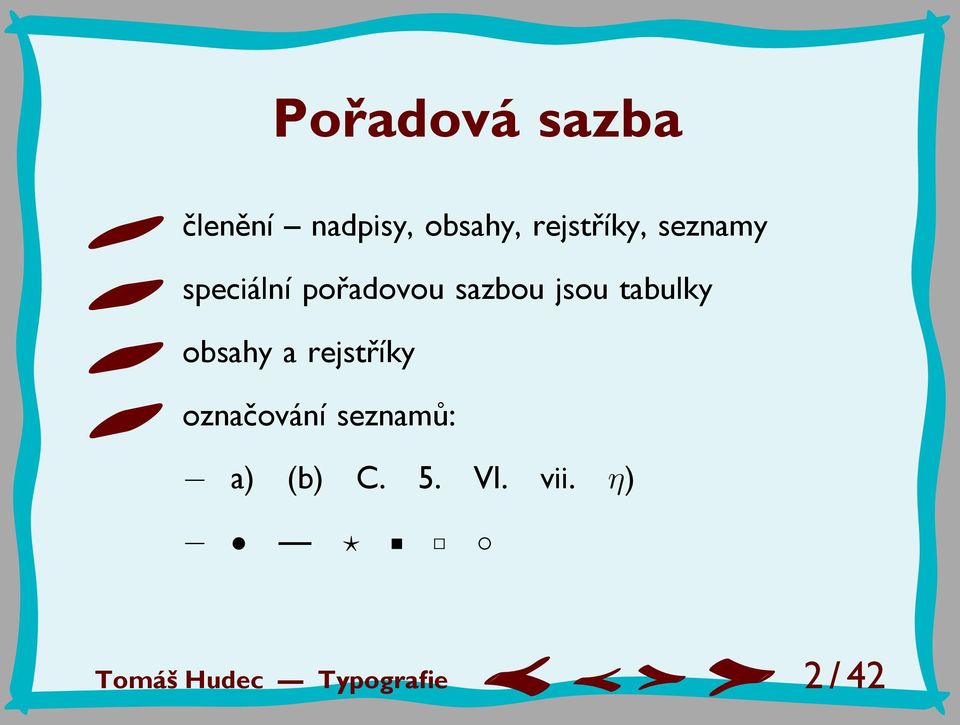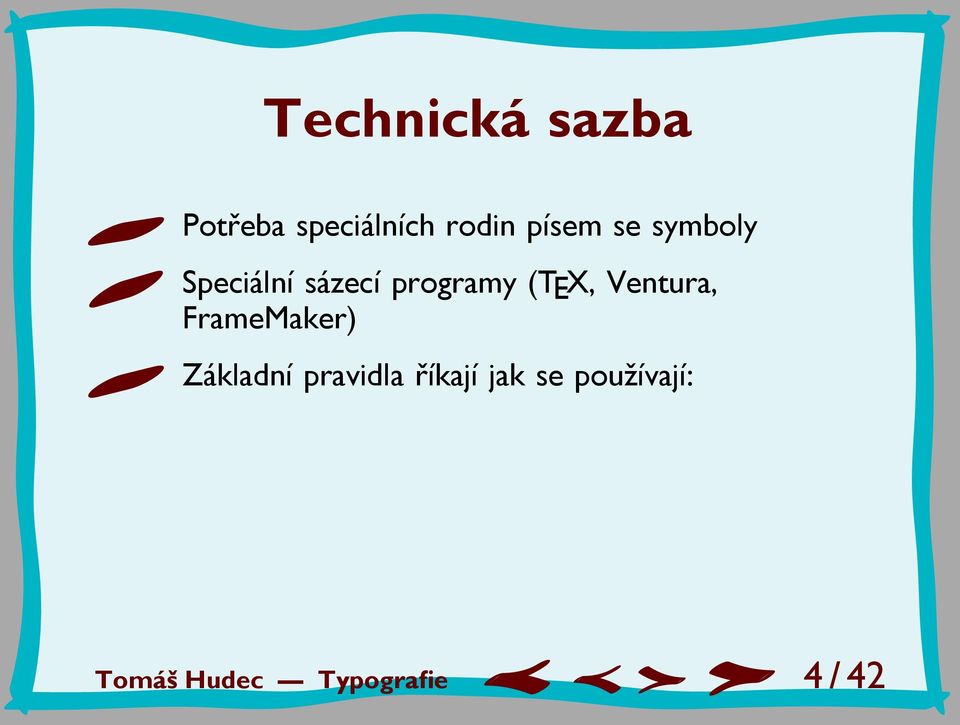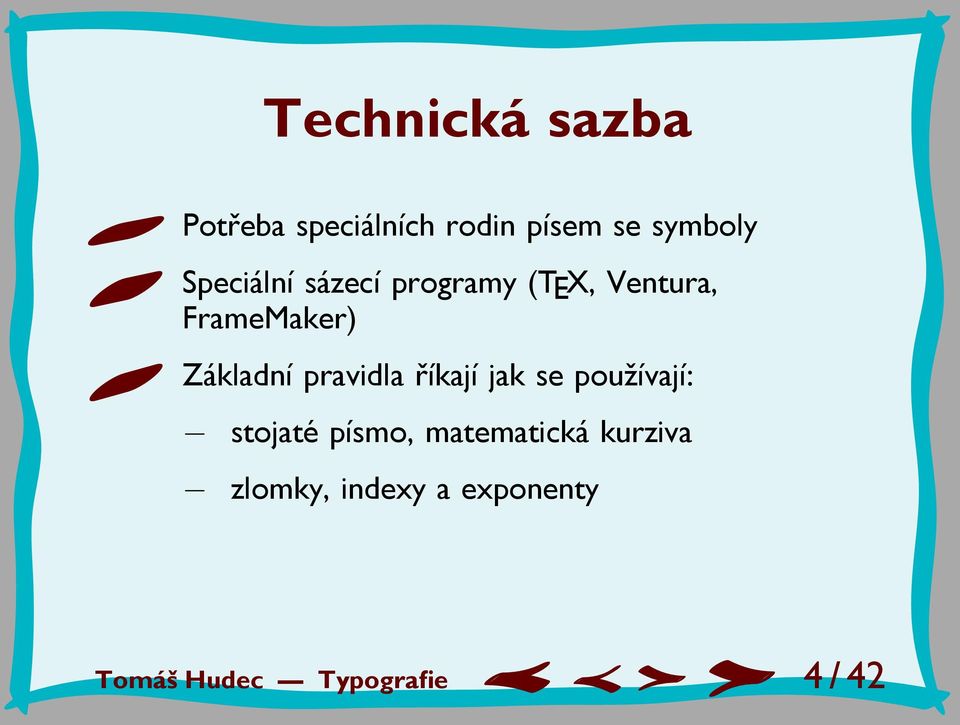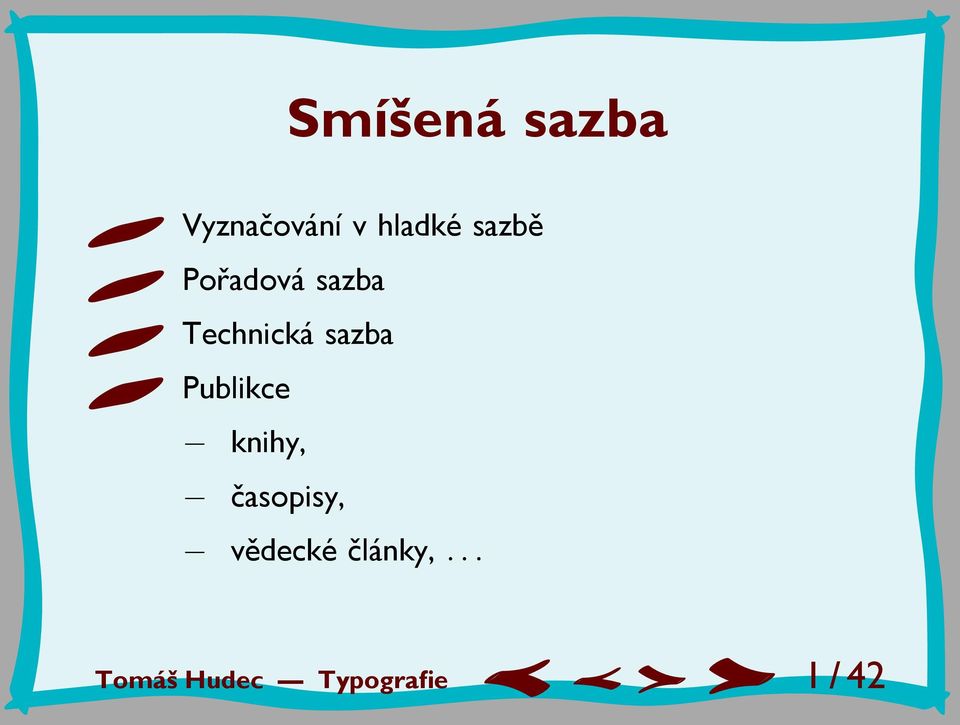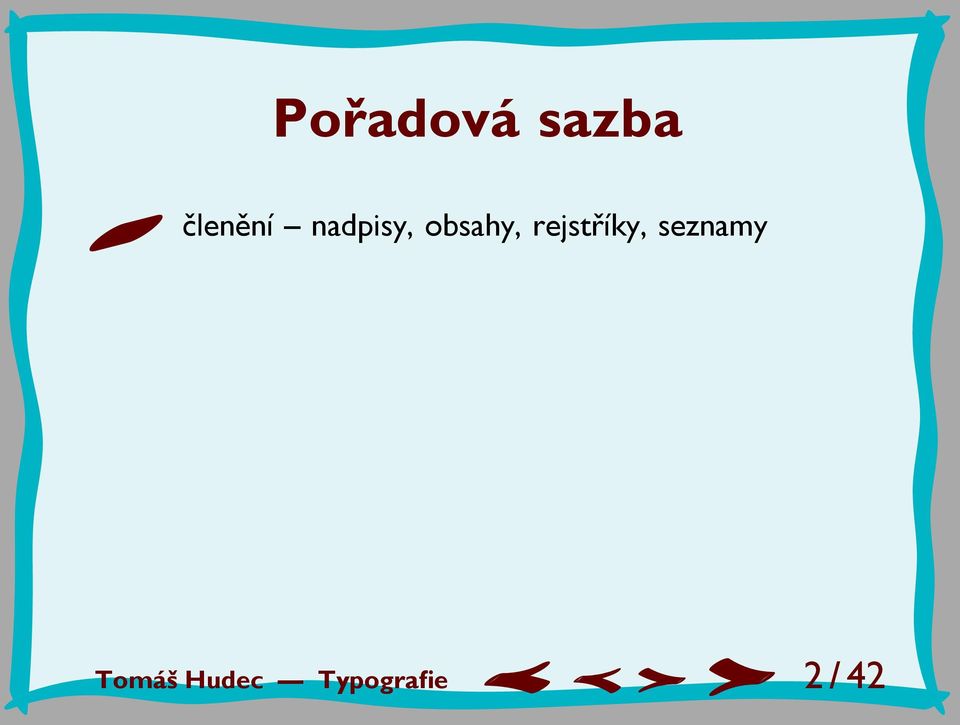
Typografie. Smíšená sazba, kniha
1 Typografie Smíšená sazba, kniha
2 Smíšená sazba Vyznačování v hladké sazbě Tomáš Hudec Typografie 1 / 42
3 Smíšená sazba Vyznačování v hladké sazbě Pořadová sazba Tomáš Hudec Typografie 1 / 42
4 Smíšená sazba Vyznačování v hladké sazbě Pořadová sazba Technická sazba Tomáš Hudec Typografie 1 / 42
5 Smíšená sazba Vyznačování v hladké sazbě Pořadová sazba Technická sazba Publikce knihy, Tomáš Hudec Typografie 1 / 42
6 Smíšená sazba Vyznačování v hladké sazbě Pořadová sazba Technická sazba Publikce knihy, časopisy, Tomáš Hudec Typografie 1 / 42
7 Smíšená sazba Vyznačování v hladké sazbě Pořadová sazba Technická sazba Publikce knihy, časopisy, vědecké články,... Tomáš Hudec Typografie 1 / 42
8 Smíšená sazba Vyznačování v hladké sazbě Pořadová sazba Technická sazba Publikce knihy, časopisy, vědecké články,... Akcidenční sazba Tomáš Hudec Typografie 1 / 42
9 Pořadová sazba členění nadpisy, obsahy, rejstříky, seznamy Tomáš Hudec Typografie 2 / 42
10 Pořadová sazba členění nadpisy, obsahy, rejstříky, seznamy speciální pořadovou sazbou jsou tabulky Tomáš Hudec Typografie 2 / 42
11 Pořadová sazba členění nadpisy, obsahy, rejstříky, seznamy speciální pořadovou sazbou jsou tabulky obsahy a rejstříky Tomáš Hudec Typografie 2 / 42
12 Pořadová sazba členění nadpisy, obsahy, rejstříky, seznamy speciální pořadovou sazbou jsou tabulky obsahy a rejstříky označování seznamů: a) (b) C. 5. VI. vii. η) Tomáš Hudec Typografie 2 / 42
13 Zarovnání seznamů Vpravo a) raz b) dva. m) třináct Vlevo a) raz b) dva. m) třináct 1. raz 2. dva. 13. třináct I. raz II. dva. XIII. třináct Tomáš Hudec Typografie 3 / 42
14 Technická sazba Potřeba speciálních rodin písem se symboly Tomáš Hudec Typografie 4 / 42
15 Technická sazba Potřeba speciálních rodin písem se symboly Speciální sázecí programy (TEX, Ventura, FrameMaker) Tomáš Hudec Typografie 4 / 42
16 Technická sazba Potřeba speciálních rodin písem se symboly Speciální sázecí programy (TEX, Ventura, FrameMaker) Základní pravidla říkají jak se používají: Tomáš Hudec Typografie 4 / 42
17 Technická sazba Potřeba speciálních rodin písem se symboly Speciální sázecí programy (TEX, Ventura, FrameMaker) Základní pravidla říkají jak se používají: stojaté písmo Tomáš Hudec Typografie 4 / 42
18 Technická sazba Potřeba speciálních rodin písem se symboly Speciální sázecí programy (TEX, Ventura, FrameMaker) Základní pravidla říkají jak se používají: stojaté písmo, matematická kurziva Tomáš Hudec Typografie 4 / 42
19 Technická sazba Potřeba speciálních rodin písem se symboly Speciální sázecí programy (TEX, Ventura, FrameMaker) Základní pravidla říkají jak se používají: stojaté písmo, matematická kurziva zlomky Tomáš Hudec Typografie 4 / 42
20 Technická sazba Potřeba speciálních rodin písem se symboly Speciální sázecí programy (TEX, Ventura, FrameMaker) Základní pravidla říkají jak se používají: stojaté písmo, matematická kurziva zlomky, indexy a exponenty Tomáš Hudec Typografie 4 / 42
21 Technická sazba Potřeba speciálních rodin písem se symboly Speciální sázecí programy (TEX, Ventura, FrameMaker) Základní pravidla říkají jak se používají: stojaté písmo, matematická kurziva zlomky, indexy a exponenty ostatní symboly Tomáš Hudec Typografie 4 / 42
22 Technická sazba Potřeba speciálních rodin písem se symboly Speciální sázecí programy (TEX, Ventura, FrameMaker) Základní pravidla říkají jak se používají: stojaté písmo, matematická kurziva zlomky, indexy a exponenty ostatní symboly mezery Tomáš Hudec Typografie 4 / 42
23 Technická sazba písmo Stojaté písmo: běžné číslice a indexy (také třeba e nebo i) Tomáš Hudec Typografie 5 / 42
24 Technická sazba písmo Stojaté písmo: běžné číslice a indexy (také třeba e nebo i) značky jednotek (m, h, s, V, N, W) Tomáš Hudec Typografie 5 / 42
25 Technická sazba písmo Stojaté písmo: běžné číslice a indexy (také třeba e nebo i) značky jednotek (m, h, s, V, N, W) znaky funkcí a operátory (log, ln, sin, lim, max) Tomáš Hudec Typografie 5 / 42
26 Technická sazba písmo Stojaté písmo: běžné číslice a indexy (také třeba e nebo i) značky jednotek (m, h, s, V, N, W) znaky funkcí a operátory (log, ln, sin, lim, max) závorky, operace, relace (+,,, /, :, =, <, >) Tomáš Hudec Typografie 5 / 42
27 Technická sazba písmo Stojaté písmo: běžné číslice a indexy (také třeba e nebo i) značky jednotek (m, h, s, V, N, W) znaky funkcí a operátory (log, ln, sin, lim, max) závorky, operace, relace (+,,, /, :, =, <, >) Matematická italika: proměnné a běžné značky (a, x, F ) Tomáš Hudec Typografie 5 / 42
28 Matematický text 1 π π = 0 cos(nϕ z sin ϕ) dϕ = ( z n+2p ( 1) 2) p p=0 p! (n + p)! Zapsáno v TEXu: $${1\over\pi}\int_0^\pi \cos(n\phi-z\sin\phi)\,{\rm d}\phi = \sum_{p=0}^\infty \left(z\over2\right)^{n+2p} {(-1)^p\over p!\,(n+p)!}$$ Tomáš Hudec Typografie 6 / 42
29 Tvorba knihy Příprava zrcadla stránek Tomáš Hudec Typografie 7 / 42